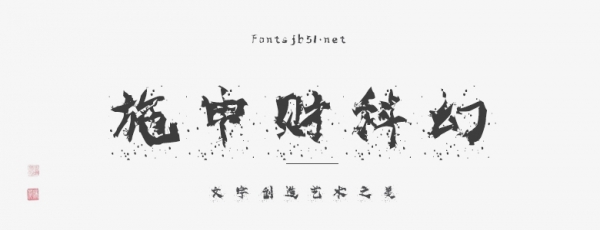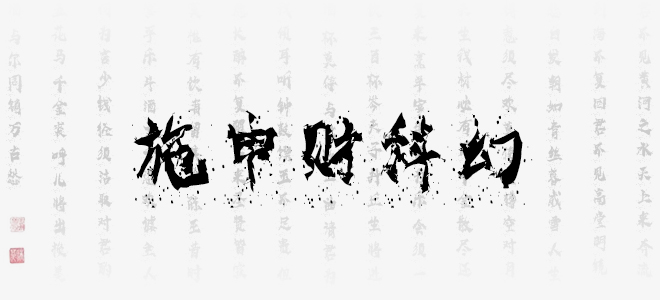
施申財(cái)科幻是施申財(cái)字庫(kù)中一款非常個(gè)性的書(shū)法藝術(shù)字體,字體筆畫(huà)隨性,結(jié)構(gòu)灑脫自在,具有很好的視覺(jué)感,適合于文化類(lèi)的宣傳設(shè)計(jì)、商業(yè)類(lèi)品牌的廣告和產(chǎn)品包裝設(shè)計(jì)以及個(gè)性化文字排版等較多場(chǎng)景。
施申財(cái)科幻